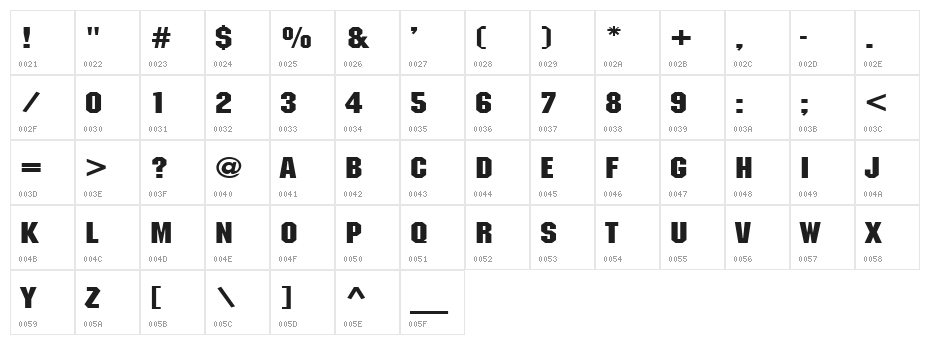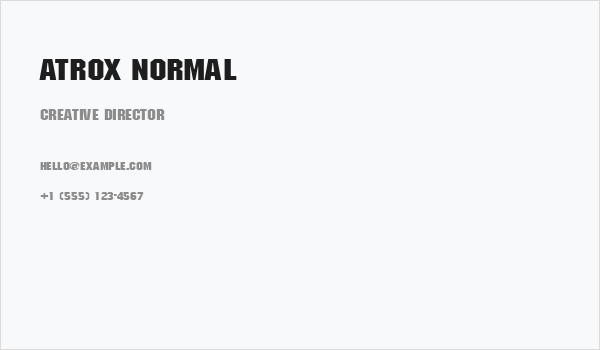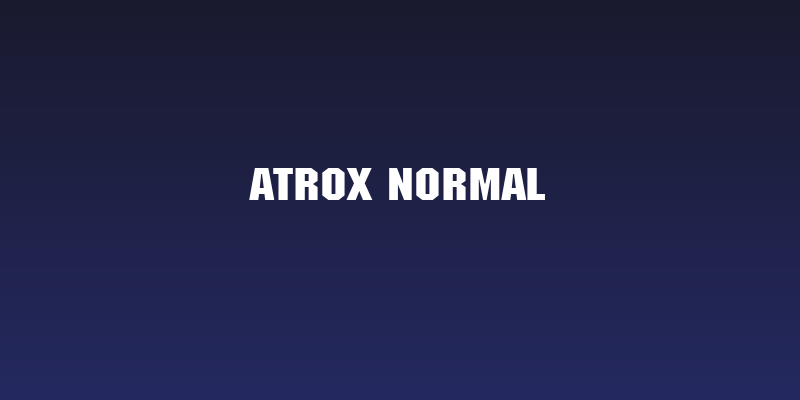
ATROX normal Font
| Progetti proposti | This font is perfect for branding projects, poster designs, sports team logos, and any application where a bold, assertive typeface is needed. |